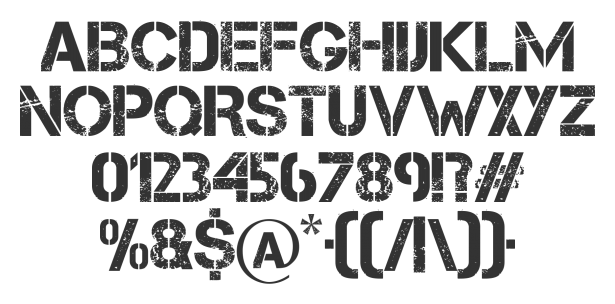
Шрифт военный русский: Армейские (военные) киррилические шрифты
Этот шрифт был разработан на основе стандартов APP-6. Он включает в себя основные символы и, как и Wingdigs, представляет собой набор символьных (не буквенных) знаков.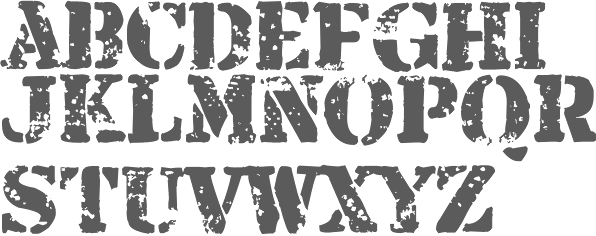